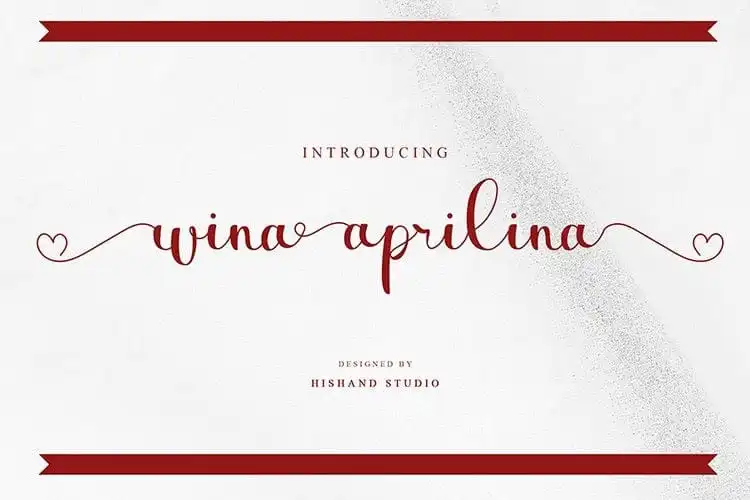
Wina aprilina Calligraphy Font – Fonte Grátis
Wina aprilina Calligraphy Font
Introduzimos uma elegante fonte de script chamada “Wina Aprilina Calligraphy Font”, especialmente concebida para eventos românticos como aniversários de casamento e feriados do Valentine. Esta fonte especial é um ícone para designers de gráficos em busca de personalidade, oferecendo uma vasta gama de alternativas abertas com terminações suaves que permitem uma letração fantástica. A Wina Aprilina Calligraphy Font é perfeita não apenas para criar marcas d’água e logotipos atraentes, mas também para uso em anúncios publicitários, postagens nas redes sociais, embalagens de produtos e até mesmo no design das roupas. Com certeza ela será uma excelente escolha para quem procura um toque elegante e romântico em seus projetos gráficos. A Wina Aprilina é a fonte perfeita para aqueles que buscam manter os sentimentos de amor e romance em cada projeto.